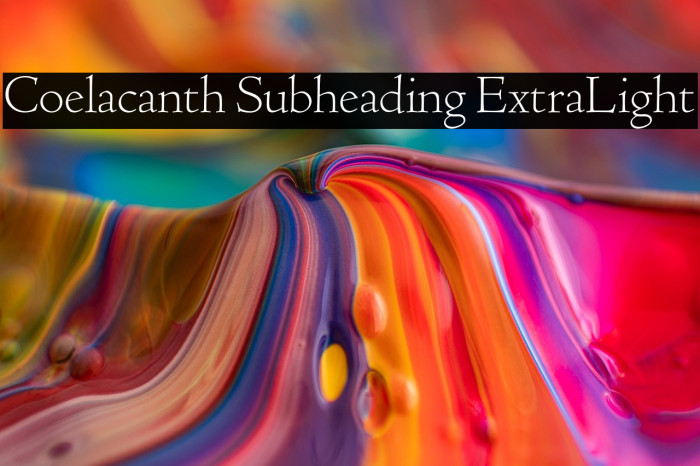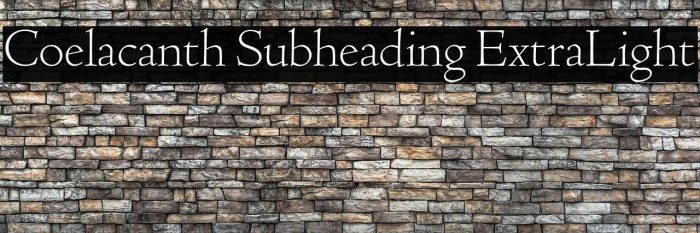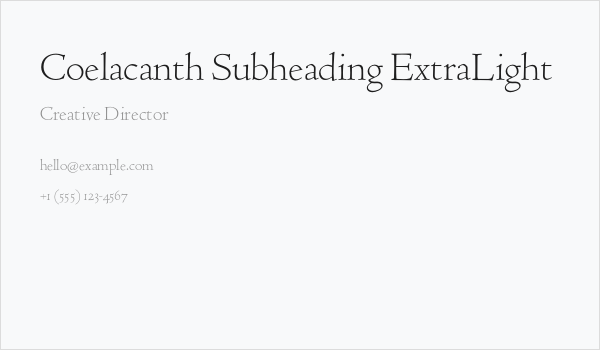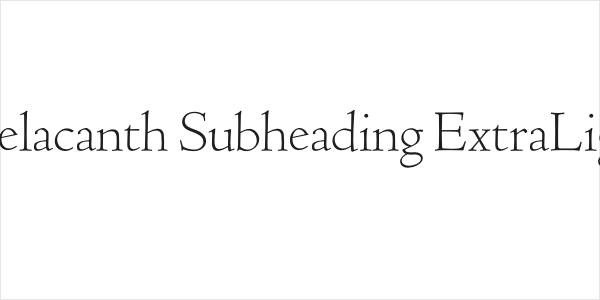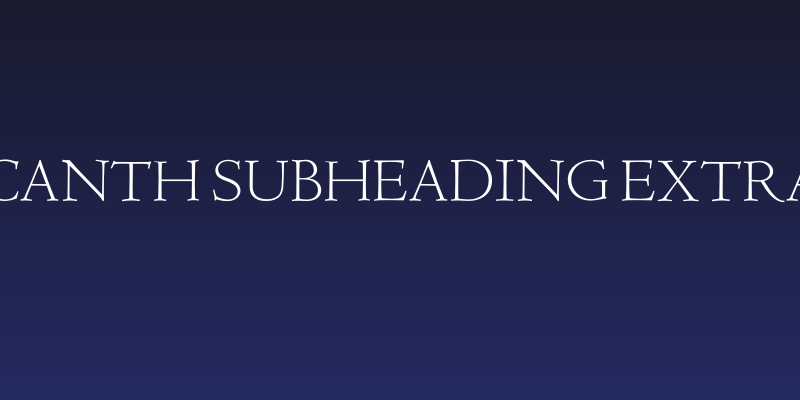
Coelacanth Subheading ExtraLight Font
✎ Serif
| Kategorien | Serif |
| Gesamtstil | Classic |
| Anwendungsfall | Headlines, Logos, Editorial design |
| Vorgeschlagene Projekte | Ideal for wedding invitations, luxury branding, editorial design, and elegant packaging. |